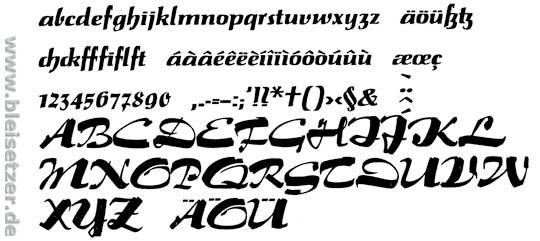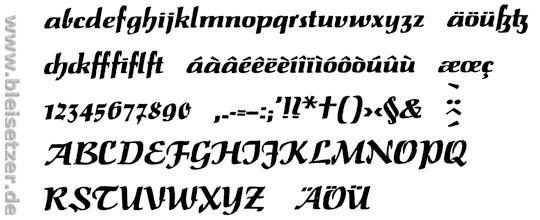
Logo-Schrift für Mukkeband
ich bin dabei, ein Logo für meine Band zu entwickeln, "The Dorfband Crackerjacks". Wir werden für Partys, Hochzeiten etc. gebucht und spielen dort alle gängigen Rock- und Schlager-Klassiker von Mendocino bis Rocking All Over The World.
Jetzt bin ich dabei, die Homepage für die Truppe zusammenzubasteln. Als gelernter Mediengestalter eigentlich nicht das Problem, allerdings fehlt mir jegliche Idee für die Logoschrift.
Ich hatte vor, die gesamte Seite ein wenig auf retro und grunge zu trimmen (nichts passt besser zu der Art Musik ;) ), als grafische Elemente könnte ich mir Zigarettenkippen, alte Schallplatten und Eintrittskarten aus den 30er-Jahren vorstellen.
Bei dem Logo selbst hemmt mich auch die Länge der Wörter. Verwende ich für "Dorfband" und "Crackerjacks" jeweils eine eigene Schrift? Setze ich die Wörter neben- oder übereinander? Und welche Schriften passen?
Verwende ich für "Dorfband" und "Crackerjacks" jeweils eine eigene Schrift?
Davon würde ich abraten. Wenn ich das richtig verstehe, soll ja eine gewisse Ironie und Selbstdistanz dadurch ausgedrückt werden, daß das bobenständige »Dorfband« mit »Crackerjacks« in einem einzigen Begriff verbunden wird. Wenn man nun unterschiedliche Schriften verwendet, dann fallen die beiden mühsam zusammengefügten Begriffe vollends auseinander und »Dorfband« wird nur noch als Attribut zu »Crackerjacks« wahrgenommen, nicht mehr als Bestandteil des Bandnamens.
Okay, in die Richtung hatte ich auch schon überlegt. Das mit der Ironie entspricht genau dem Charakter, den das Logo haben soll (und mit dem wir auf die Bühne gehen).
Dann wäre ich für Font-Vorschläge offen...
Oder etwas, das auf den ersten Blick gar nicht passt – vielleicht eine besonders elegante Anglaise?
Schonmal gar nicht schlecht... welche Schriften sind das?
Eventuell noch ein bisschen mehr mit "Show"-Charakter, wenn ihr versteht, was ich meine...
Das denke ich auch... mit „Showcharakter“ meine ich auch eher den Look, den Stevo auf seinen alten Plakaten zum Vorschein gebracht hat. Habe auch schon viel mit freien „Grunge“-Fonts rumprobiert, da fehlt mir aber der klassische Charakter. Das Ganze sollte also schon in Stevos Richtung gehen oder aber an typische „Show“-Logos wie in aktuellen MediaMarkt-Spots etc. angelehnt sein.
Die Tannenberg hat mir da zu wenig Aussagekraft.
Danke für den Vorschlag (du versuchst ja mit allen Mitteln, mich von der Tannenberg zu überzeugen ;) ).
Das kommt dem ganzen schon recht nahe, allerdings sieht die Tannenberg so aus, als würden wir Werbung für einen Alpenmilch-Riegel machen... ;)
Naja, macht die APPD werbung für Alpenmilchriegel? Die haben glaub ich auch Tanneberg...
Kann mir jemand sagen, welche Schriftarten auf den Plakaten von Stevo benutzt werden?
da ist viel handgezeichnet, du kannst aber
auf myfonts.com begriffe wie retro oder art deco in die suchmaske
eingeben und sich umschauen.
sonst würde ich die foundrys empfehlen
Wie willst Du denn Swing- und Jazz-Musik mit einer deutschen "Dorfband Crackerjacks" vereinbaren?
Löge deren Dorf irgendwo in Virginia, würde ich das ja noch nachvollziehen können, aber so?
Also ich würde den Schriftzug vom Stil her ins Ende der 50er Jahre legen, mit solch einem Anhauch:
Nur halt mit den symbolischen Bildern aus dem Deutschland der damaligen Zeit. Rock'nRoll, Peticoats, ironisch gezeigte Tanzschulen-Abschlußball. Ein bißchen deutsche Elvis-Versionen wie Ted Herold, Peter Kraus. Ein bißchen unschuldigen Sex wie Conny Froebess und so. Die Jungs mit hochgeschlagenem Kragen an der Nietenjacke und einer Entenschwanz-Frisur.
Ja, ich glaube, ich würde damit beginnen, mit der Salto, besser noch: mit der Saltino, zu spielen. Outline-Versionen davon zu erstellen, Pastell-Farben für den Hintergrund.
Gesamteindruck:
Unbeschwert, unschuldig, fröhlich, optimistisch.
"Wir sind wieder wer. Wir schaffen das schon."
Nina Hagen hatte mal eine Platte mit solchen Texten und in diesem Stil. "Ich hab' den Farbfilm vergessen..." und solche Sachen.
Nein, die verwenden Koch Fraktur.
Danke für die vielen Anregungen und Beispiele. Ich habe mich letztendlich in die Bello von Underware verliebt und damit ein in meinen Augen sehr gutes Logo entworfen.
Was meint ihr?